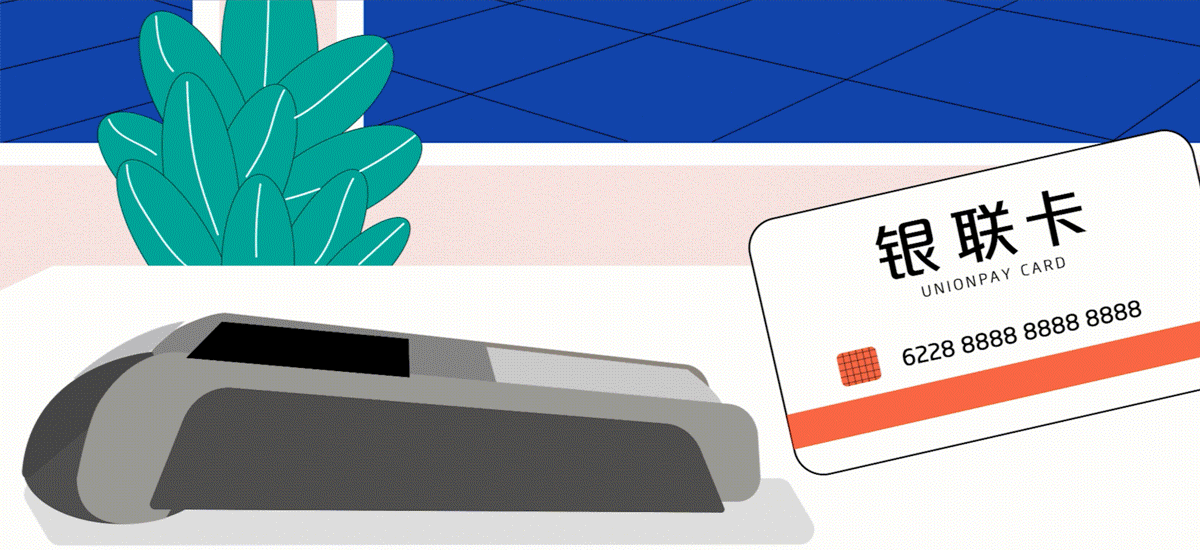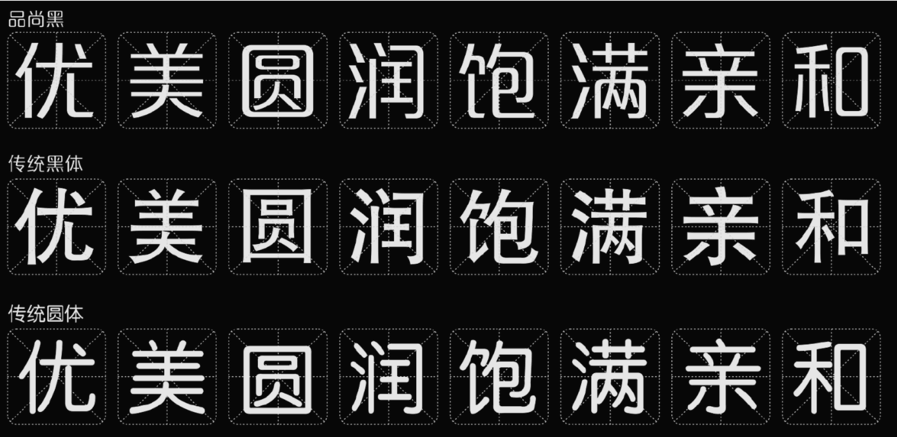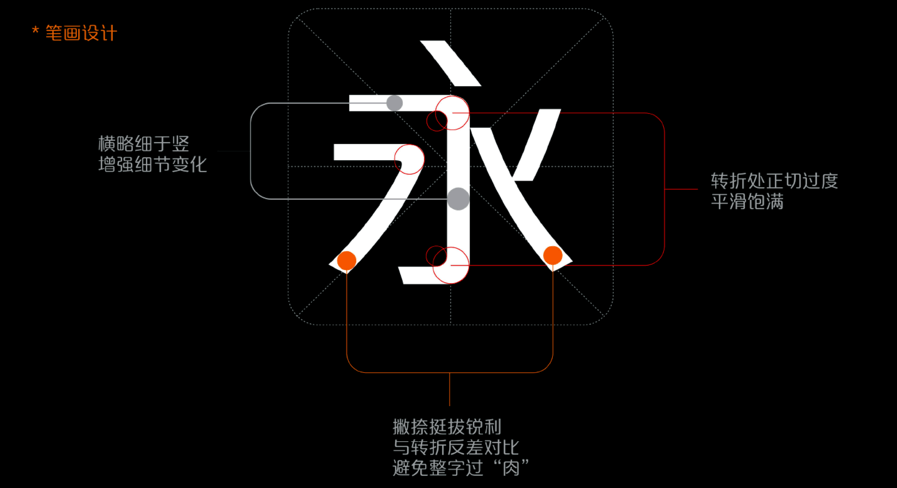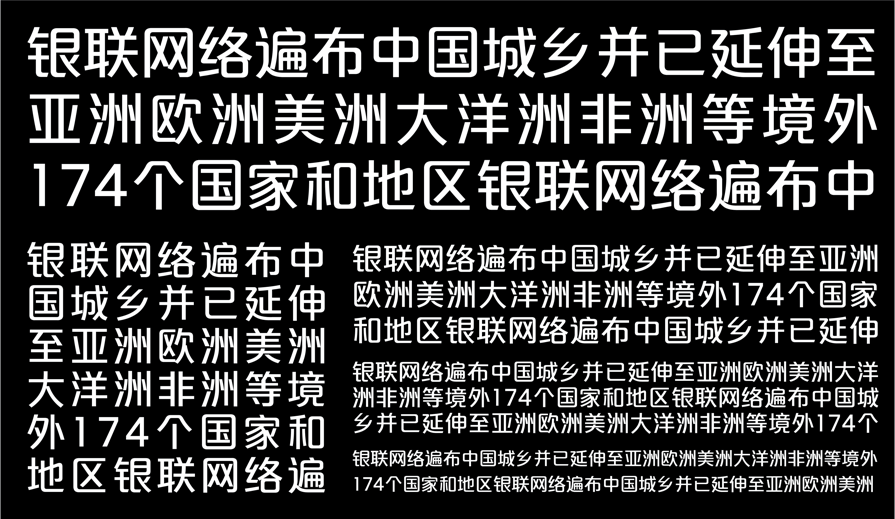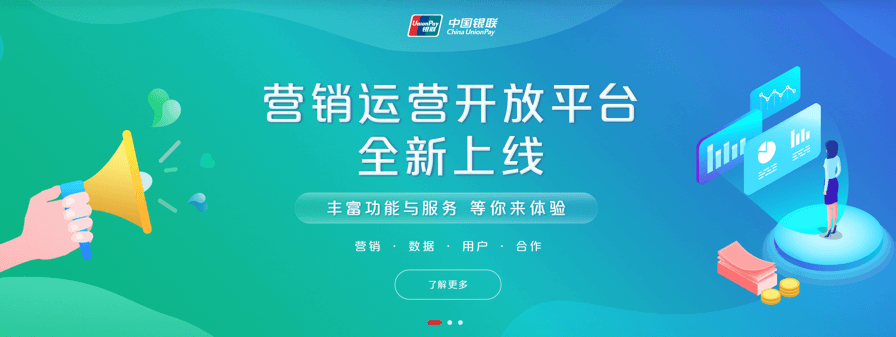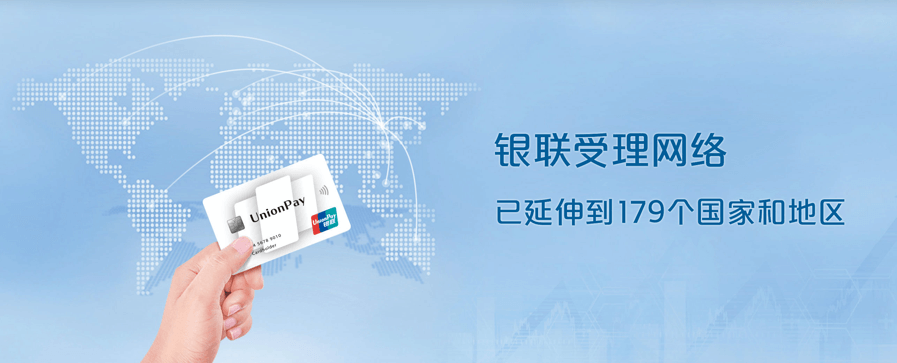
中国银联
品牌定制字体
方正品尚黑系列字体
2011
品尚黑系列是为银联定制的系列字体。在遵循“银联”标志设计原则和整体风格的同时,又保证了与银联品牌视觉形象的高度统一。字体系列化设计,不但适用于银联企业视觉形象传达要素;也适用于广告文案标题、正文使用。银联专用字体,不仅成为银联企业视觉识别系统中重要的核心要素,更是对银联品牌形象强有力的延展。
方正品尚黑系列字体结构舒展饱满,避免了传统黑体聚集的特点,字体不会形成黑块,同时结合了黑体和圆体的优点,字体特点突出。横略细于竖,增强细节变化,撇捺挺拔锐利,与转折反差对比,避免整字过“肉”,转折处正切过度,平滑饱满。
品尚黑实际应用场景